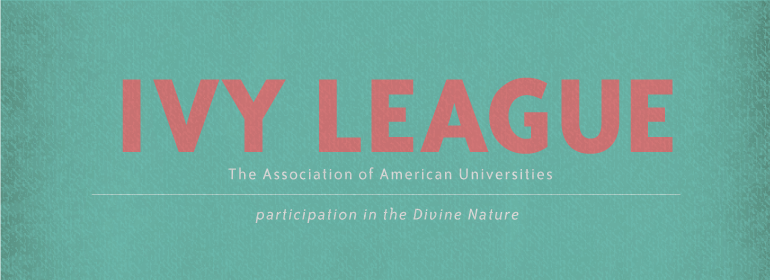
ITC Bailey™ Sans
ITC Bailey™ Sans,这款字体结构工整、笔画清晰,兼顾美观与易读性,适用于标题、正文、海报、包装、LOGO 等多种场景。字形优雅稳定,风格百搭耐看,适配日常排版与创意设计,让文字呈现更舒适、更具质感。ITC Bailey™ Sans一笔一画,皆是细节,以均衡的比例、流畅的线条打造舒适视觉体验,字形端正大气,风格简约现代。无论是商业设计、品牌宣传还是日常排版,都能轻松驾驭,让文字更有格调与力量。ITC Bailey™ Sans字体下载。
字体品牌: ITC(Monotype) 设计师:Bailey,Kevin 字体分类:无衬线体 字体属性:外文 字符集:Unicode 发布时间: 2018